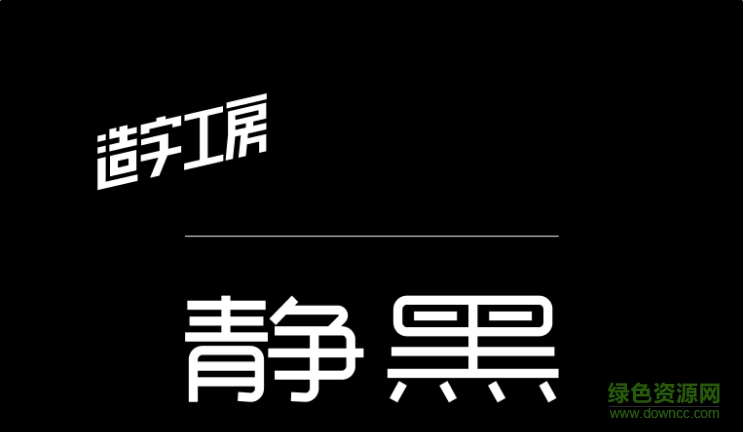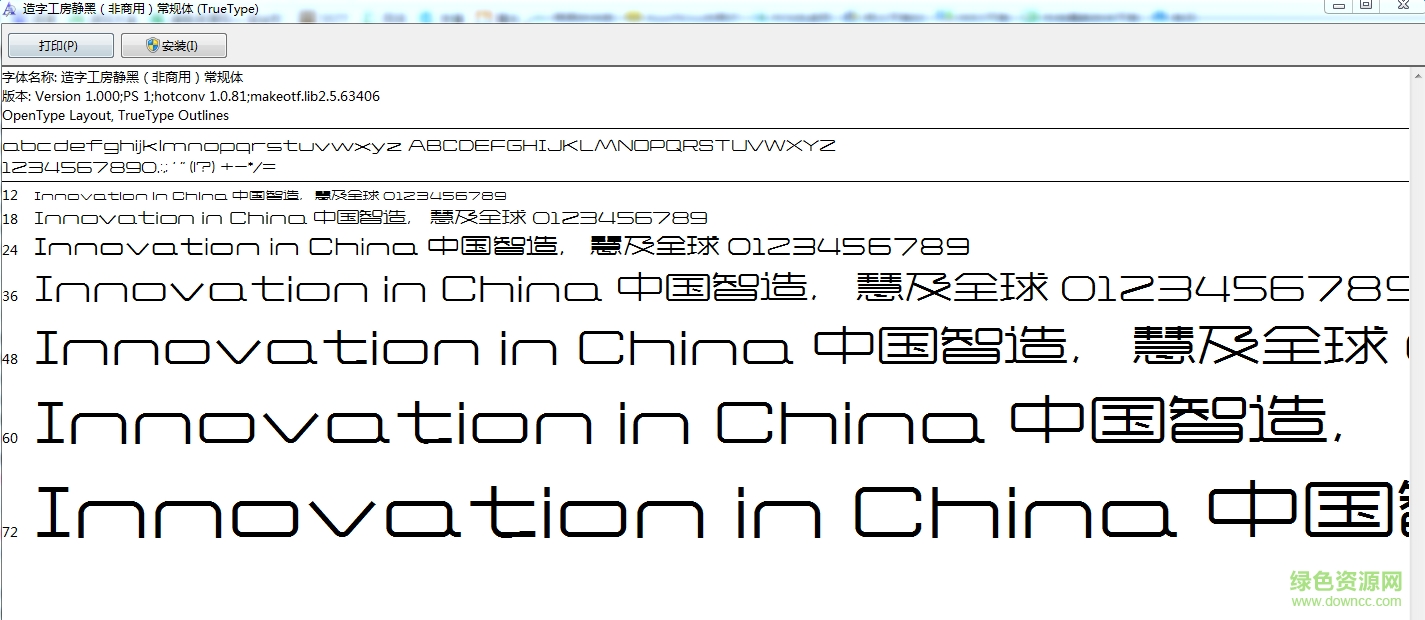
造字工房靜黑體是一款造字工房類清新簡潔風(fēng)格字體軟件,靜黑字體一筆一劃直爽有力,整體效果顯得扁平有創(chuàng)意,深受廣大書法家喜愛,還有更多好看字體歡迎來綠色資源網(wǎng)下載體驗(yàn)!
造字工房靜黑體,其字形扁平,此款字體在黑體字形基礎(chǔ)之上巧妙創(chuàng)新,筆畫纖細(xì)、簡潔有力、字形簡約、風(fēng)格明顯且易于閱讀。結(jié)構(gòu)清晰緊密而內(nèi)斂,給人清新脫俗之感。